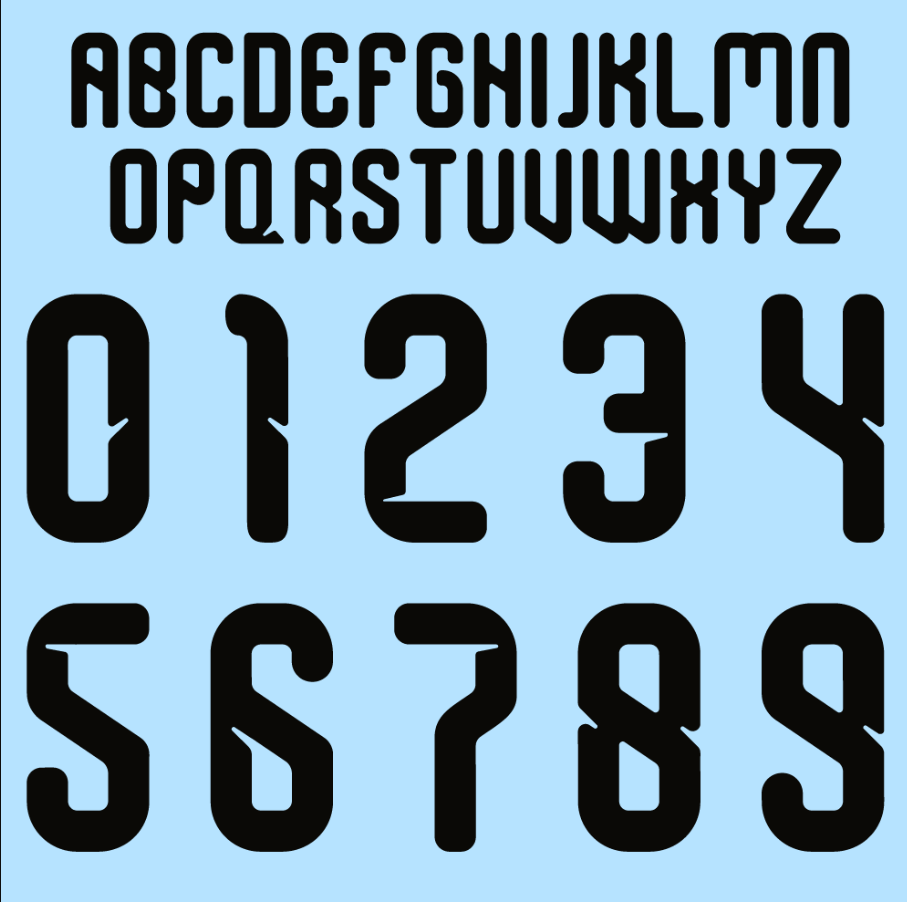
Quando o assunto é design esportivo, a Seleção Japonesa (JFA) nunca decepciona. Preparando-se para o maior palco do futebol mundial nos EUA, México e Canadá, a parceria entre a Adidas e os “Samurais Azuis” entrega mais uma vez uma tipografia que mistura modernidade com elementos culturais.
Estilo Visual: Tradição e Futuro
A tipografia da Adidas para o Japão no ciclo da Copa 2026 rompe com o padrão genérico. Inspirada na estética streetwear de Tóquio e na precisão das katanas, a fonte apresenta cortes angulares agressivos e uma estrutura “blocky” (blocada).
O visual transmite velocidade e precisão, características marcantes do time asiático. Nos uniformes, ela se destaca tanto na versão titular (azul índigo) quanto na reserva, garantindo legibilidade e uma identidade visual única que a diferencia das outras seleções patrocinadas pelas três listras.